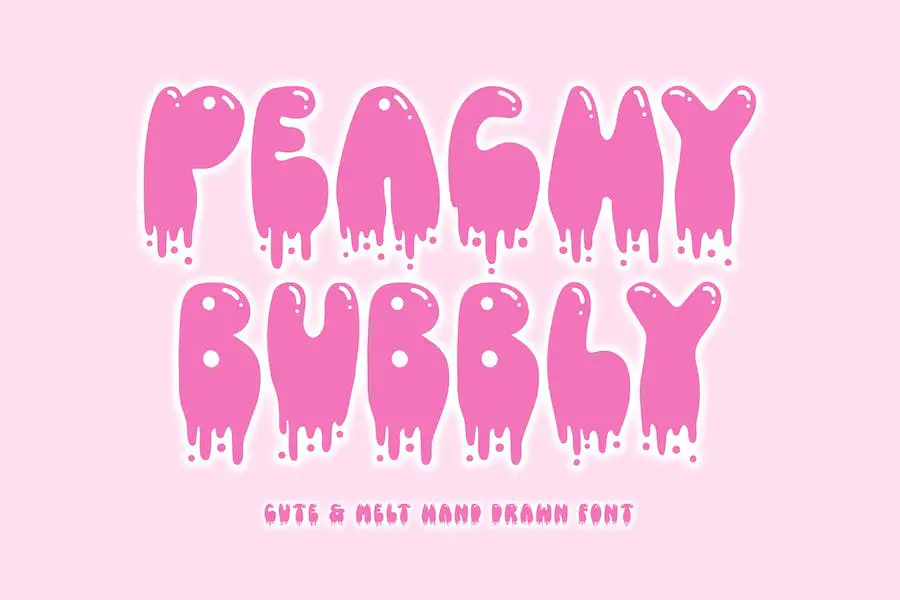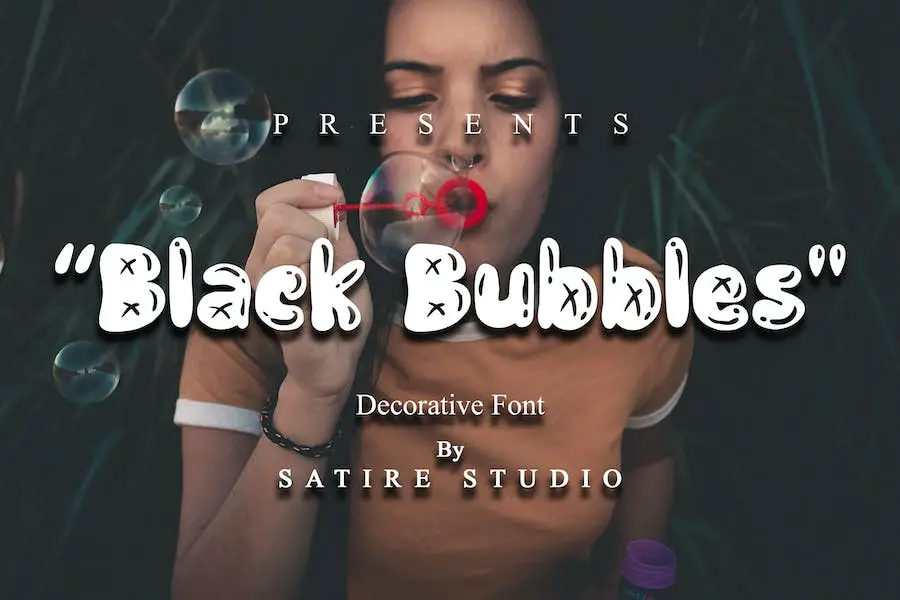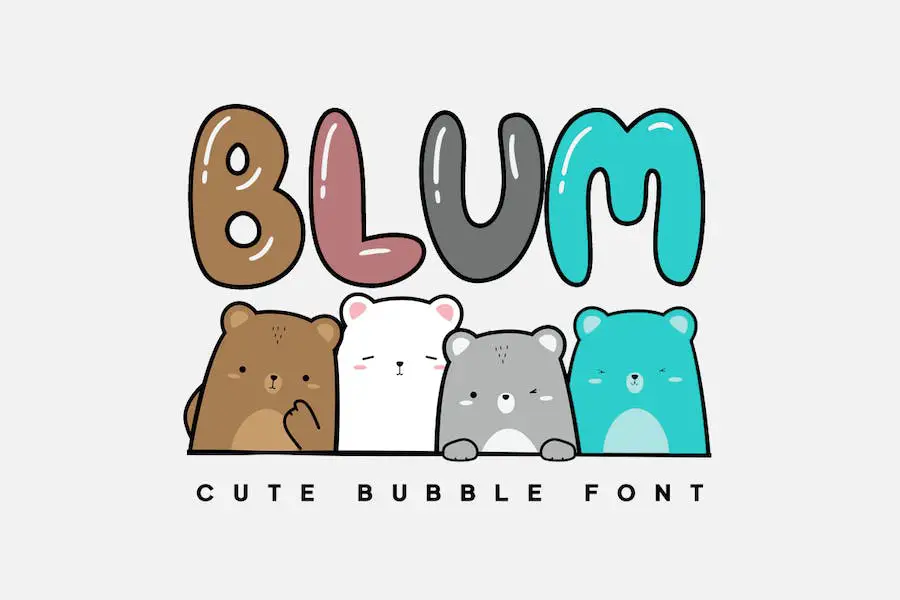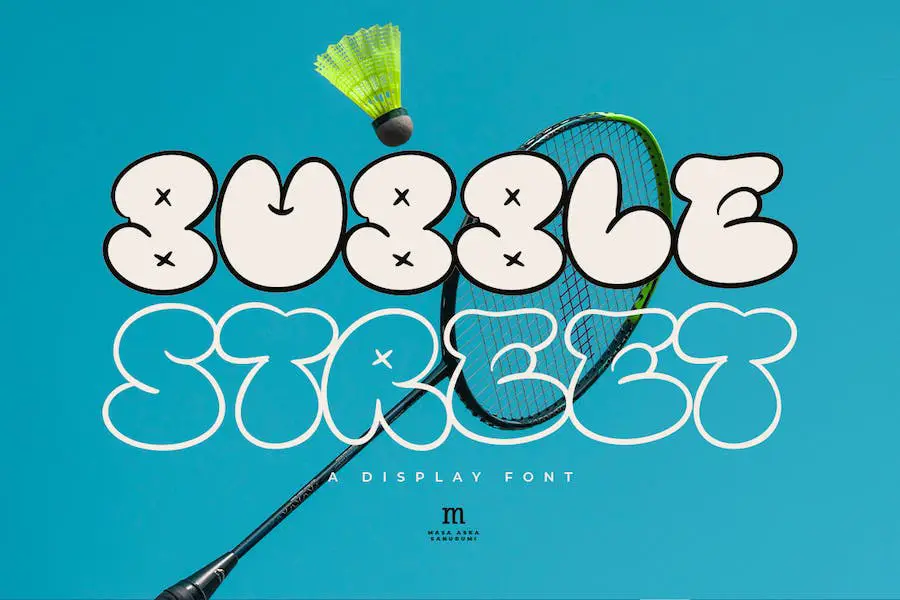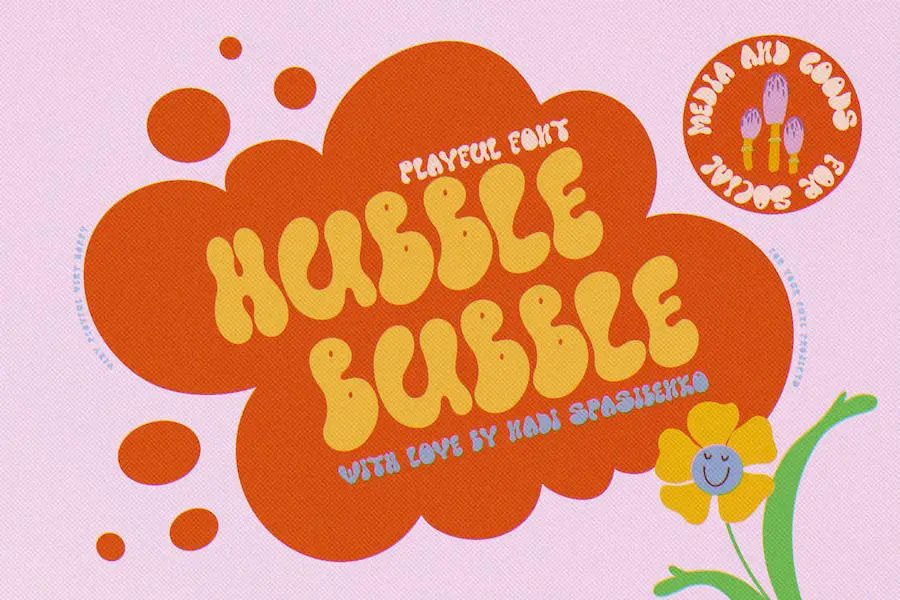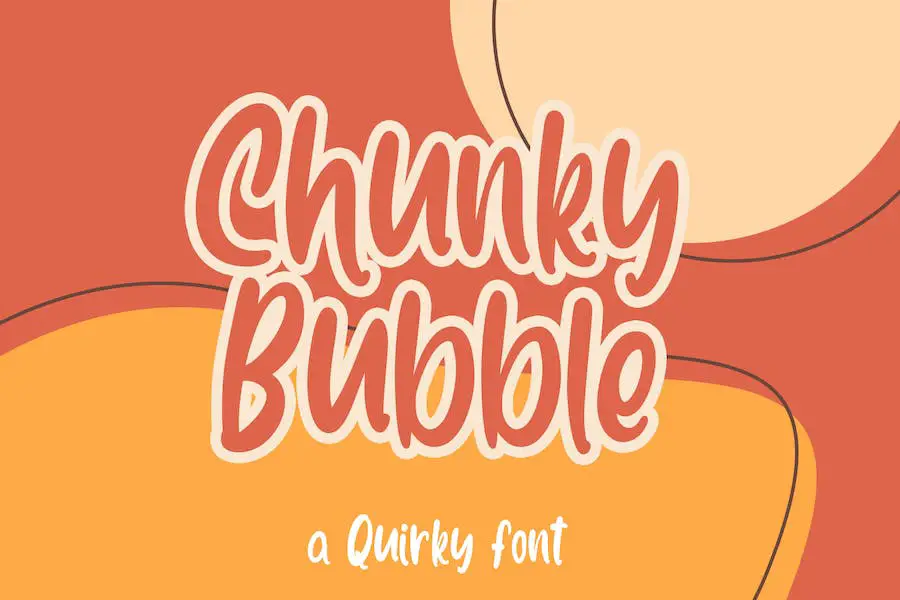
Veröffentlicht: 2023-08-04Sind Sie Grafikdesigner und möchten Ihren Projekten einen Hauch von Laune und Verspieltheit verleihen? Wenn ja, sind Sie hier richtig. In diesem Blogbeitrag erkunden wir die 27 besten Bubble-Schriftarten, die nicht nur das Design Ihrer Projekte verbessern, sondern auch ein Gefühl von Lebendigkeit und Spaß in Ihre Arbeit bringen.
Nun fragen Sie sich vielleicht: Was genau sind Blasenschriften? Nun, es handelt sich um eine Schriftart, die das Aussehen von Blasen oder Luftballons nachahmt.
Diese Schriftarten haben abgerundete Kanten, sanfte Kurven und ein schönes, sprudelndes Aussehen, wodurch sie perfekt geeignet sind, Ihren Designs einen zusätzlichen Hauch von Kreativität zu verleihen.
Aber warum sollten Sie die Verwendung von Blasenschriften in Betracht ziehen? Die Antwort ist einfach: Sie können die Stimmung Ihrer Designs sofort verbessern.
Unabhängig davon, ob Sie an einem Poster, einem Logo oder einer Social-Media-Grafik arbeiten, kann die Verwendung von Blasenschriften ein Gefühl von Freude und Verspieltheit erzeugen und Ihr Design aus der Masse hervorheben.
Nachdem wir nun die Bedeutung von Bubble-Schriftarten und ihre Fähigkeit, Ihre Designprojekte zu verbessern, herausgefunden haben, wollen wir uns mit den 27 besten Bubble-Schriftarten befassen, deren Integration in Ihre Arbeit Sie unbedingt in Betracht ziehen sollten.
Beste Premium-Blasenschriften
Möchten Sie Ihren Designs einen Hauch von Spaß und Verspieltheit verleihen? Dann sind Sie bei unserer Auswahl der besten Premium-Bubble-Schriftarten genau richtig, die garantiert jedem Projekt Leben und Laune verleihen.
Blasenbildung
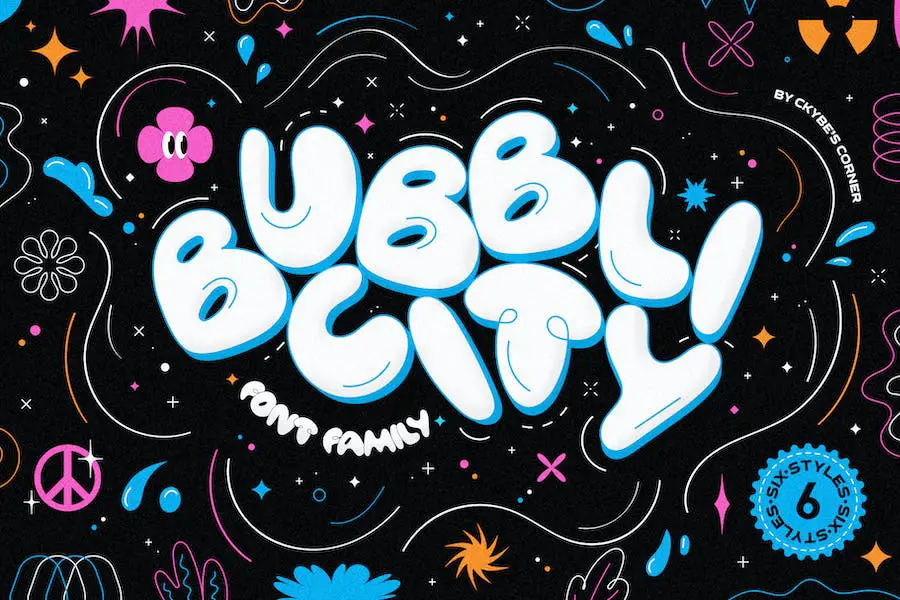
Bubblicity – Die verspielte Schriftfamilie, die Sie in die nostalgische Ära der 90er und 2000er zurückversetzt. Mit ihren 6 einzigartigen Stilen, einschließlich Farboptionen, ist diese Blasenschrift perfekt, um Ihren Designprojekten einen lustigen und Retro-Touch zu verleihen.
Inspiriert von Straßengraffiti verfügt diese Schriftart über Linienelemente, die sich mühelos einfügen und einen dynamischen und auffälligen Effekt erzeugen. Ob Sie Poster, Social-Media-Beiträge, Einladungen oder sogar ein Logo erstellen, Bubblicity ist eine vielseitige Wahl, die Ihre Kunstwerke mit Sicherheit aufwerten wird.
Eines der herausragenden Merkmale dieser Schriftart ist die Möglichkeit, mit den Buchstabenabständen zu spielen, da jeder Buchstabe nahtlos mit den anderen überlappt. Erschließen Sie noch mehr kreative Möglichkeiten, indem Sie mit mehreren Mischoptionen und Farbänderungen im Farbton/Sättigungsbereich experimentieren.
Und für einen zusätzlichen Hauch von Dimension sollten Sie die Verwendung von Abschrägungs- und Prägeeffekten in Betracht ziehen. Bubblicity bietet endlose Möglichkeiten, Ihre Designs zum Leben zu erwecken. Warum also warten? Genießen Sie die verspielte Atmosphäre dieser Schriftart und lassen Sie Ihrer Kreativität freien Lauf!
Blasenglanz
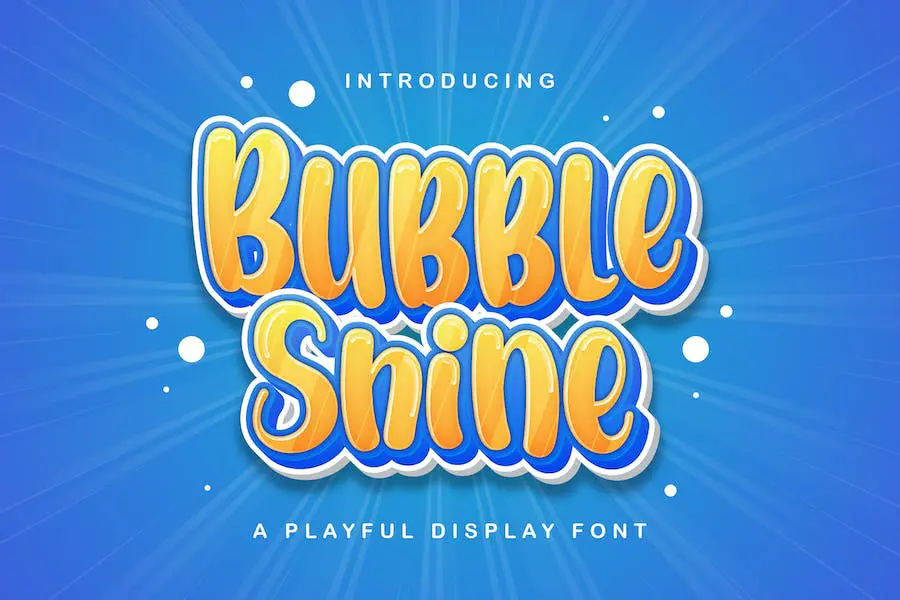
Bubble Shine ist eine verspielte Display-Schriftart, die sich perfekt dazu eignet, Ihren Projekten eine lustige und frische Note zu verleihen. Durch die Mehrsprachigkeit sowie Groß- und Kleinschreibung bietet diese Schriftart vielfältige Möglichkeiten für Ihre kreativen Gestaltungen.
Egal, ob Sie an einem Kinderprojekt oder einer Schulaufgabe arbeiten, Bubble Shine wird mit Sicherheit ein Statement setzen.
Bubble Shine ist nicht nur mit gängigen Designsoftwares wie Adobe Illustrator, Adobe Photoshop und Adobe InDesign kompatibel, sondern funktioniert auch nahtlos mit Microsoft Word. Dies bedeutet, dass Sie diese Schriftart problemlos in Ihre Digital- und Druckprojekte integrieren können.
Lizadah
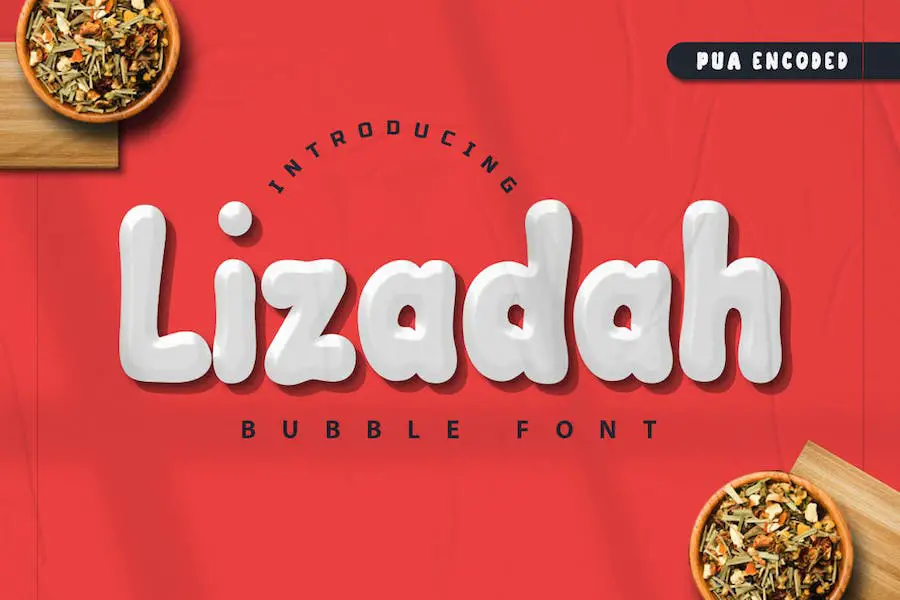
Lizadah ist eine fantastische Blasenschrift, die jedem Designprojekt eine coole, trendige und sprudelnde Atmosphäre verleiht. Mit ihrem verspielten und authentischen Stil ist diese Schriftart die perfekte Wahl für Kinderaktivitäten oder Schulprojekte.
Diese Schriftart ist in verschiedenen Dateiformaten erhältlich, darunter WOFF, TTF und OTF, sodass sie leicht zugänglich und mit verschiedenen Designsoftware kompatibel ist. Egal, ob Sie an einer Website, einem Poster oder einem Logo arbeiten, Lizadah sorgt für einen Hauch von Spaß und Kreativität.
Die Lizadah-Schriftart enthält alle erforderlichen Dateien in einem, was die Verwendung bequem und problemlos macht. Sie müssen sich keine Gedanken über die Suche nach verschiedenen Dateien oder Kompatibilitätsprobleme machen.
Zuckerblase
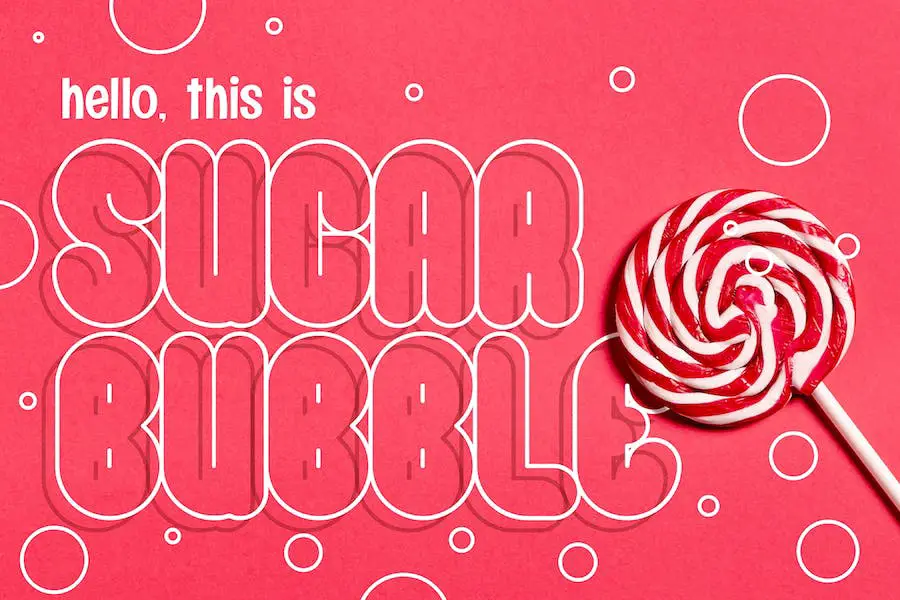
Sugar Bubble ist eine entzückende Displayschrift, die jedem kreativen Projekt einen Hauch von Süße und Charme verleiht. Mit ihrer einzigartigen Wendung und dem verspielten Design ist diese Schriftart perfekt für Bastler und Grafiker, die ihrer Arbeit ein lustiges und skurriles Element hinzufügen möchten.